设计师怎么去选择一款合适的字体?
对于设计师而言,为每个设计选择合适的字体就是事半功倍了。如果你正在为选择合适的 图片字体 而感到困惑,那么今天这篇文章可以为您能轻松为设计选择合适的字体。
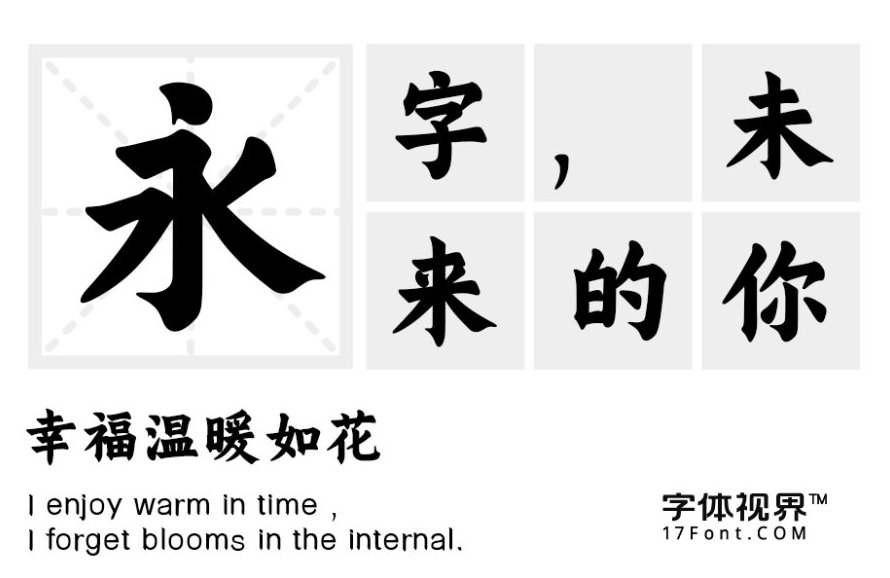
了解字体气质特征:设计师在进行设计时,字体是否运用得合适,能直接决定版面的成败。选择合适的字体能准确地传达信息和美感,但是字库字体太多不知选择哪种,或者自我感觉字体越独特才是最好看,导致画面感档次不高。因此选择字体前需要了解各字体的气质特征,才能对症下药。
匹配主题:不同种类的字体代表不同的风格样式,是文字的表现形式和风格触感。明确设计目的。例如:“面向的目标人群有哪些?设计风格是什么?是否需要和其他的设计、品牌相匹配?”等等这些问题
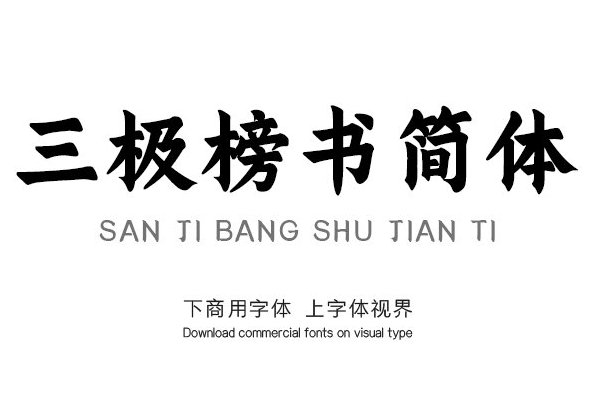
例如这款三极榜书简体,以传统楷书大字为结构雏形设计,笔画豪迈雄伟,笔墨中正,字形雍容大气,厚重沉稳,极富艺术感染力。适用于各类传统习俗的包装和宣传设计及书法作品排版标题、招牌设计。